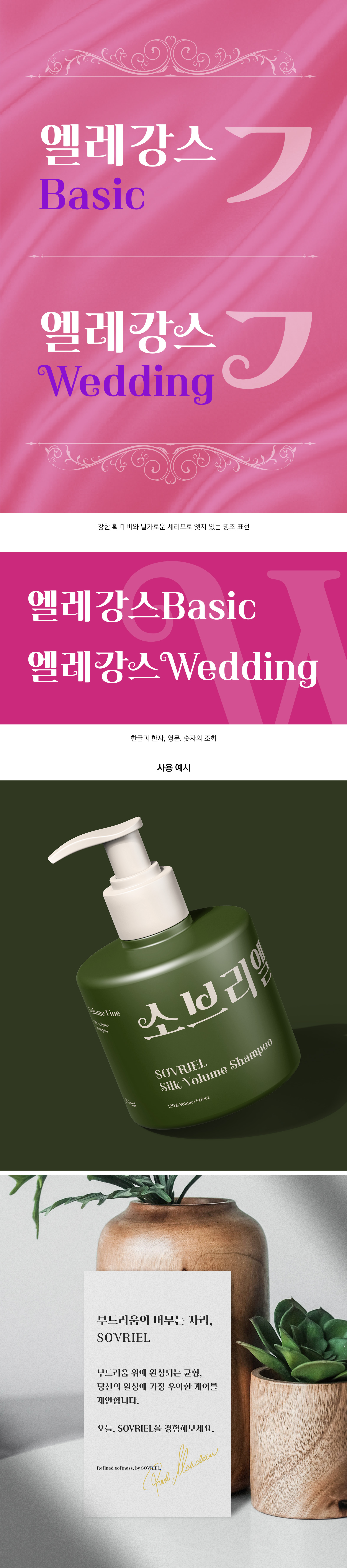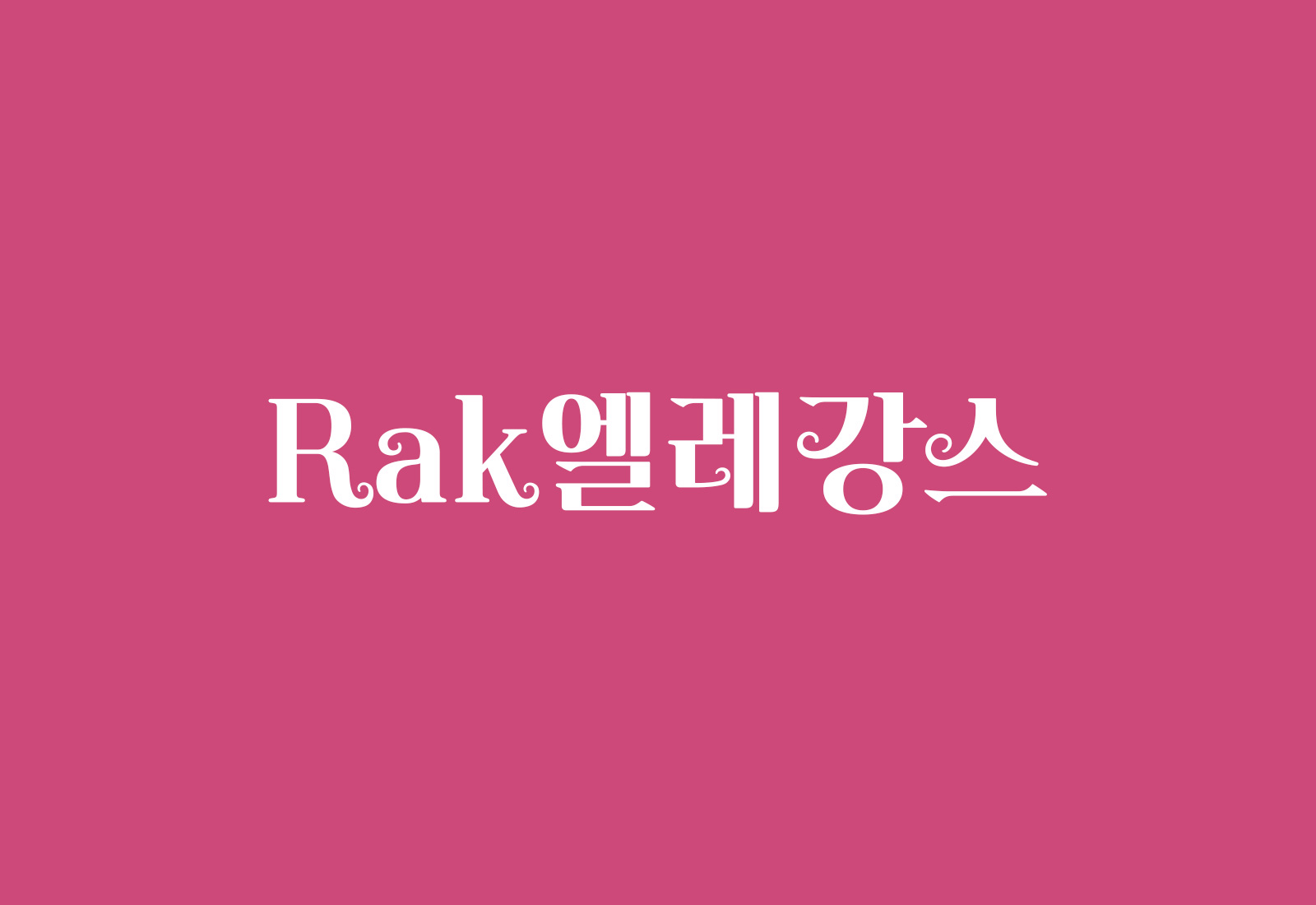
RakElegance
2 Style - Basic, WeddingRak엘레강스는 획의 대비를 섬세하게 조율해 부드러운 리듬과 우아한 흐름을 완성한 서체입니다. 전체적인 구조는 단정하게 정리하되, 획의 시작과 끝에는 은은한 곡선을 더해 고급스럽고 여성적인 인상을 강조했습니다. Basic과 Wedding 두 가지 스타일로 구성됩니다. Basic은 정제된 형태와 균형 잡힌 대비를 통해 격식 있는 인쇄물 전반에 활용할 수 있도록 설계되었고, Wedding은 리본이 자연스럽게 말리듯 이어지는 곡선 디테일을 더해 한층 로맨틱한 분위기를 담았습니다.
| FontFamily | Rak엘레강스 / RakElegance |
| Design | Park YongRak |
| Direction | Park YongRak |
- Basic
- 꽃처럼 피어나 별처럼 빛나는 그대에게
- Wedding
- 꽃처럼 피어나 별처럼 빛나는 그대에게